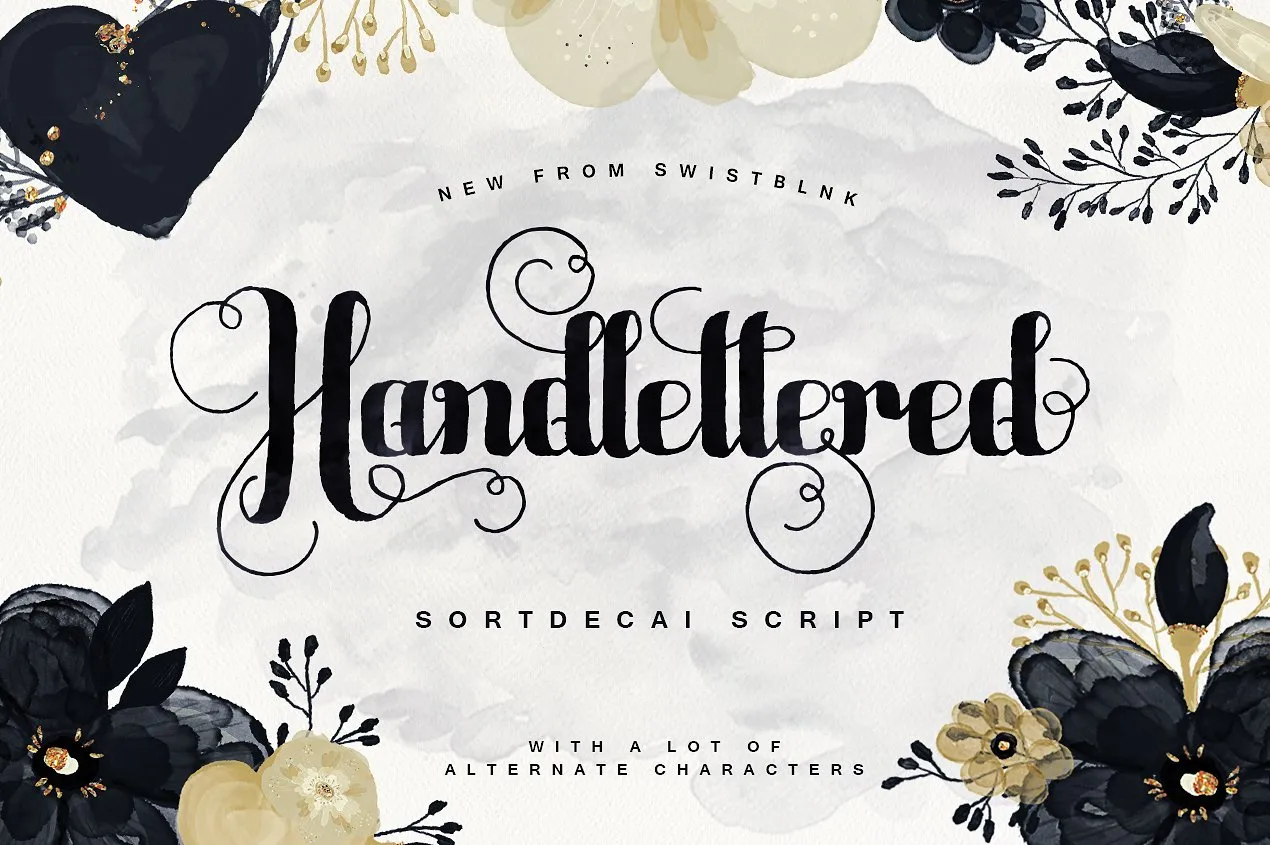
Sortdecai Script Font – Download Grátis
Sortdecai Script é uma nova adição à família Sortdecai que traz uma mistura única do modernismo com a elegância clássica do xilográfico. Esse tipo de script oferece uma experiência visual inovadora, combinando o tradicional estilo da escrita manuscrita com um toque contemporâneo e moderno. Inspirado na arte das letras antigo-góticas, Sortdecai Script é a escolha perfeita para designers que buscam dar ao seu projeto um toque de elegância sofisticada e uma sensação vintage inovadora. Com suas curvas fluidas e formas suaves, esta fonte traz a beleza dos tempos antigos à sua composição, reforçando o seu respeito pelos padrões do passado enquanto a incorpora de forma inteligente no design contemporâneo. Ideal para aplicativos como cartazes publicitários, revistas ou até mesmo websites que buscam um equilíbrio entre estética tradicional e atualidade, Sortdecai Script é uma escolha excelente para qualquer projeto onde deseja criar um impacto visual único.